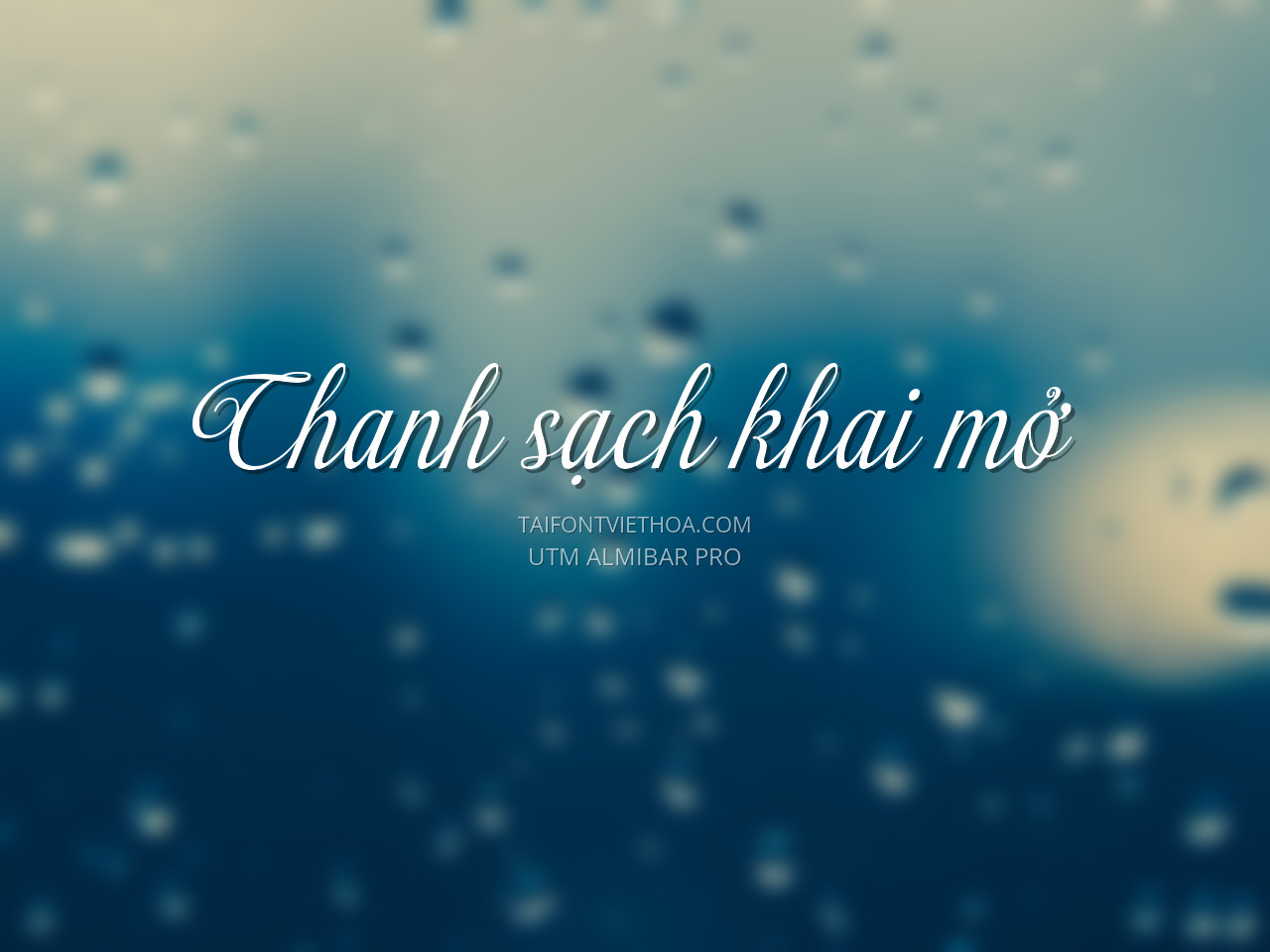
Font việt hóa UTM Almibar Pro
Giới thiệu về font UTM Almibar Pro
UTM Almibar Pro là phiên bản Việt hóa của font gốc Almibar – một kiểu chữ script cao cấp mang phong cách cổ điển và nữ tính. Font được thiết kế bởi người sáng tạo nổi tiếng Manuel Eduardo Corradine (Colombia) thuộc Corradine Fonts, và lần đầu phát hành trên MyFonts. Almibar gây ấn tượng mạnh với đường nét mảnh mai, uốn lượn nhẹ nhàng, kết hợp các yếu tố calligraphy cổ điển và hiện đại. Font hỗ trợ hơn 200 ngôn ngữ trên toàn cầu, bao gồm cả bảng mã Latin mở rộng và tiếng Việt.
Phiên bản UTM Almibar Pro đã được Việt hóa bởi Đinh Kiên – một trong những thành viên nổi bật trong cộng đồng font Việt hóa. Font hiện được chia sẻ rộng rãi trên nền tảng taifontviethoa.com, nơi quy tụ hàng ngàn bộ font Việt hóa được chọn lọc kỹ lưỡng, phục vụ cho các nhu cầu thiết kế đa dạng từ cá nhân đến doanh nghiệp. Với khả năng hỗ trợ tiếng Việt chuẩn xác, Almibar Pro mở rộng tính ứng dụng cho các dự án thiết kế mang phong cách nhẹ nhàng, lãng mạn và tinh tế.
Đặc điểm thiết kế và ứng dụng của UTM Almibar Pro
UTM Almibar Pro là font script có cấu trúc chữ mềm mại, nhiều đường uốn lượn tinh tế và độ tương phản cao giữa các nét. Phần thân chữ thường thanh mảnh, kết hợp với những đầu móc và đuôi chữ kéo dài, tạo nên phong cách thanh lịch và nữ tính. Font cũng đi kèm nhiều ligatures (kết hợp chữ cái) và ký tự thay thế giúp người dùng linh hoạt sáng tạo khi thiết kế.
Font này phù hợp cho các ứng dụng như: thiết kế thiệp cưới, bao bì mỹ phẩm, bộ nhận diện thương hiệu cao cấp, poster sự kiện, tiêu đề blog thời trang, và các ấn phẩm mang hơi hướng nghệ thuật, lãng mạn. Các ngành nghề lý tưởng gồm: tổ chức sự kiện, thời trang, mỹ phẩm, thiệp mời, wedding planner, thiết kế nội thất, nghệ thuật trình bày và truyền thông sáng tạo.